Englischer Typograf und Emailliertechniker. Geboren 1706 zu Wolverley in der englischen Grafschaft Worcester, gestorben 1775. 1726 ließ sich der ausgebildete (Grab-) Steinschneider John (Johannis) Baskerville als Schreiblehrer und Graveur in Birmingham nieder, wo er ab 1738 ein Lackierunternehmen betrieb, das auf Japanlack spezialisiert war. Sein Erfindungsgeist revolutionierte die Emailliertechnik und er machte ein Vermögen mit der Herstellung von diversen Haushaltsgegenständen.
Daneben widmete sich Baskerville seiner Passion für die Typografie, dem Buchdruck und der Korrespondenz mit bedeutenden Zeitgenossen; der amerikanische Wissenschaftler und Staatsmann Benjamin Franklin, der eine erfolgreiche Druckerei in Philadelphia errichtet hatte, zählte zu seinem engsten Freundeskreis.
Um 1754 entstand Baskervilles erster Schriftschnitt, eine in ihrer eigentlich »antibarock« 1) schlichten Linienführung bestechend elegante Vorklassizistischen Antiqua. 1757 druckte er sein erstes Buch, einen lateinischen Vergil, achtundzwanzig Seiten davon auf dem von James Whatman entwickelten, sehr weichen, »wove paper« genannten Vélin-Papier. Dafür mischte Baskerville eine spezielle Druckerschwärze und optimierte den Druckvorgang durch den Einbau von beheizten Kupferzylindern, die ein rasches Trocknen seiner tiefschwarzen Opak-Tinte bewirkten und folglich besonders exakte Konturen und ein klares Gesamtschriftbild gewährleisteten.
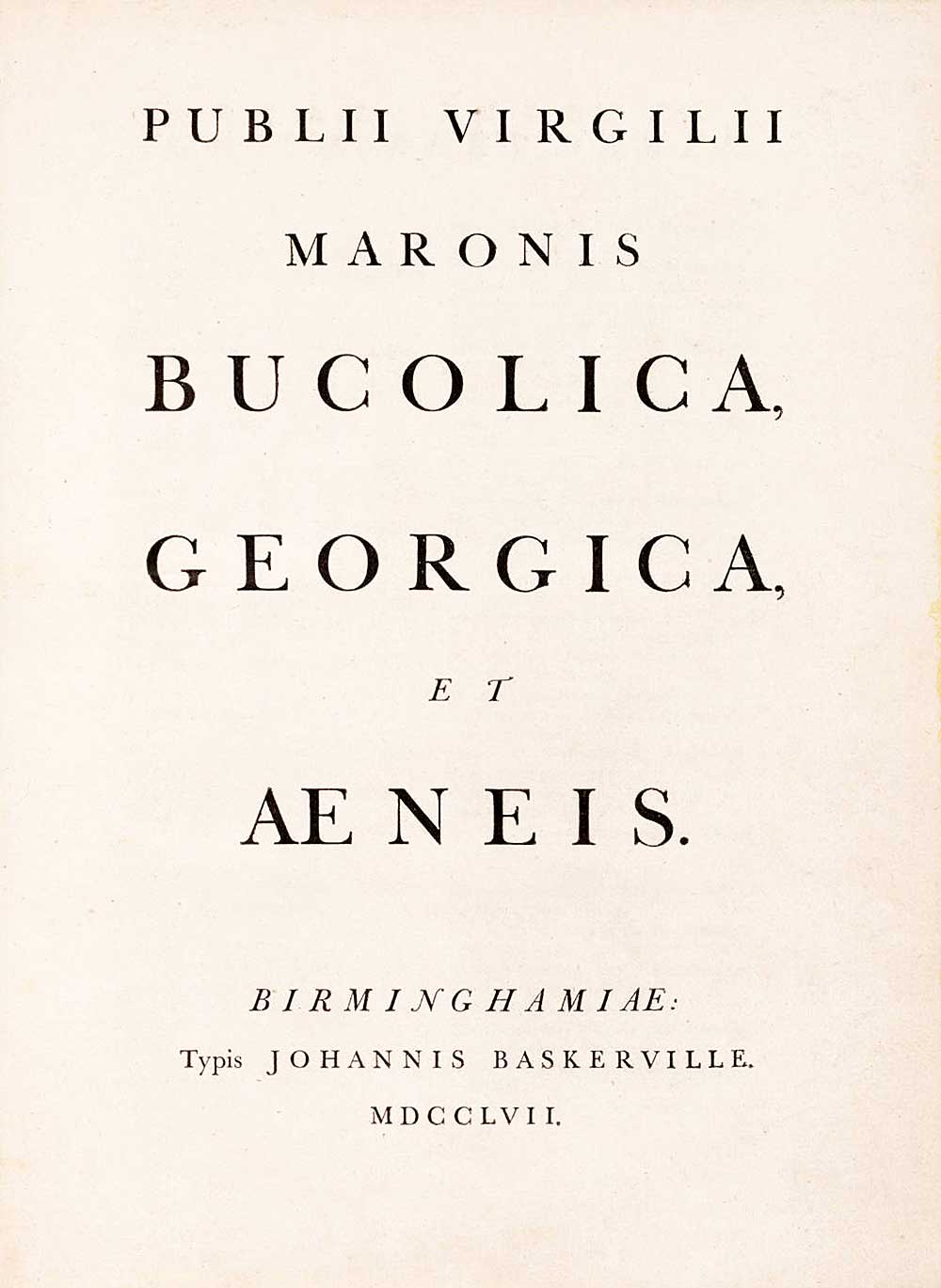
Seine Prunkedition von John Miltons Paradise Lost sicherte ihm 1758 die Ernennung zum Direktor der Cambridge University Press, für die er seine Meisterwerke, das Book of Common Prayer 1760/62 und 1763 die Bibel, druckte.
Als John Baskerville 1775 erbenlos starb, wurde der deklarierte Atheist wunschgemäß von seiner Lebensgefährtin Sarah Eaves in einem kleinen Mausoleum im acht Morgen großen Park seines feudalen Anwesens beigesetzt. Pierre Augustin Caron de Beaumarchais kaufte die Originalstempel der Antiqua um 3700 Pfund Sterling aus dem Nachlass und ließ damit die Prachtausgabe der Werke von Voltaire in 70 Bänden drucken.
Nach Sarahs Tod 1788 wechselten die Eigentümer von Baskerville House in rascher Folge. 1821 wurde Baskervilles Sarg bei Kanalgrabungen freigelegt und geöffnet. Nachdem mehrere Pfarreien eine Wiederbestattung in geweihter Erde verweigert hatten, wurde der wohlmumifizierte Leichnam Baskervilles unter anderem in den beiden größten Warenhäusern von Birmingham einem staunenden und zahlenden Publikum zur Schau gestellt.
Erst 1899 fand die bizarre Sarg-Odyssee ein Ende und John Baskerville in den Katakomben des Warstone Lane – Friedhofs in Birmingham seine endgültige Ruhestätte. 2) 3)
↑1 | Anmerkung: Verwendet man den kunstgeschichtlichen Terminus »Barock« korrekt, so ist die in Deutschland gebräuchliche Bezeichnung »Barock-Antiqua« irreführend und falsch. Denn eine »Barock-Antiqua« ist keineswegs ausschweifend, bizarr, übertrieben, verschnörkelt oder gar dekadent. Diese Schriftart sollte deshalb – so wie in Frankreich, England, Italien und in Deutschland vor 1964 üblich – als Übergangsantiqua, als Vorklassizistische Antiqua oder als Halbmediäval bezeichnet werden. In England gilt z.B. die Baskerville keineswegs als »barock« sondern als präviktorianisch. |